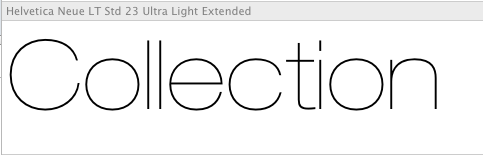
Könnte aber auch die Helvetica Neue LT Std 23 Ultra Light Extended sein.
So meinen: Es könnte auch die Linotype-Version sein.
Sollte eigentlich ne Helvetica sein - aber ich bekomme nicht heraus, welche so condensed läuft. Oder hat da vielleicht nur jemand am Zeichenabstand geschraubt? Bin für jeden Wink dankbar...
… aber ich bekomme nicht heraus, welche so condensed läuft. Oder hat da vielleicht nur jemand am Zeichenabstand geschraubt? Bin für jeden Wink dankbar...
Da hat jemand die Laufweite verringert.